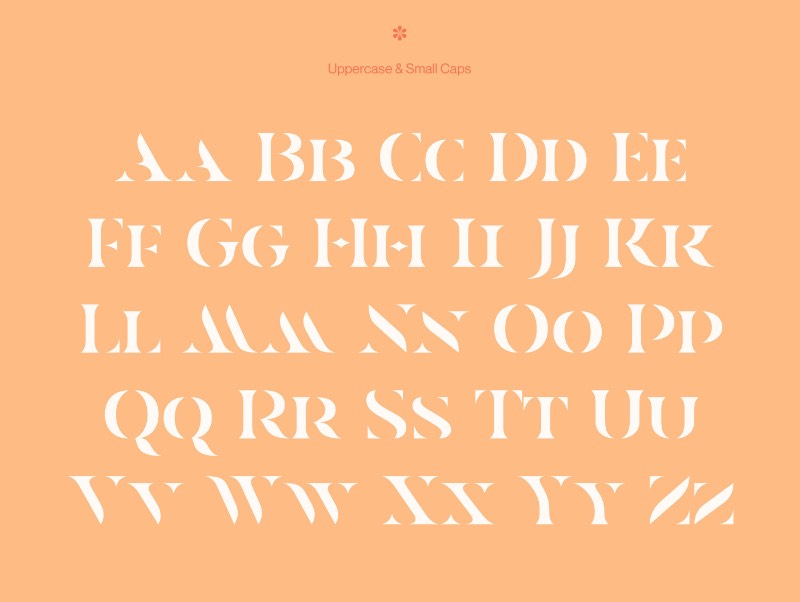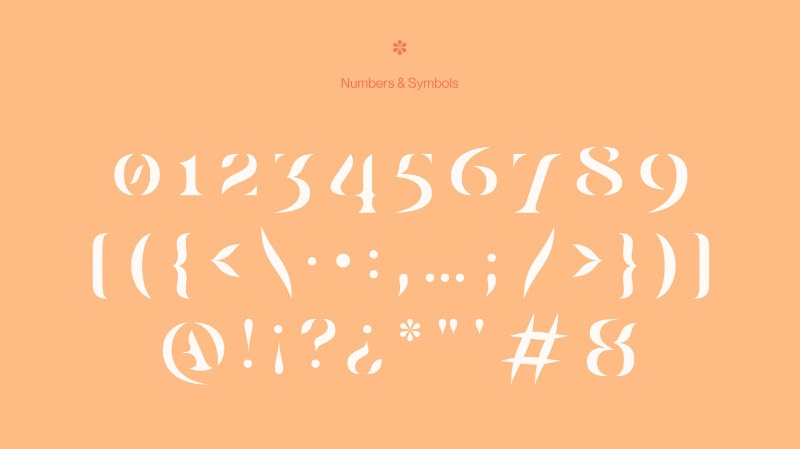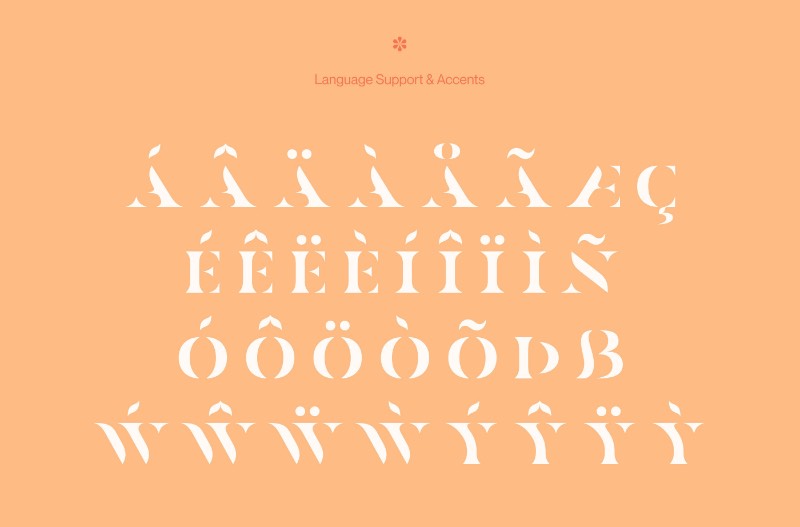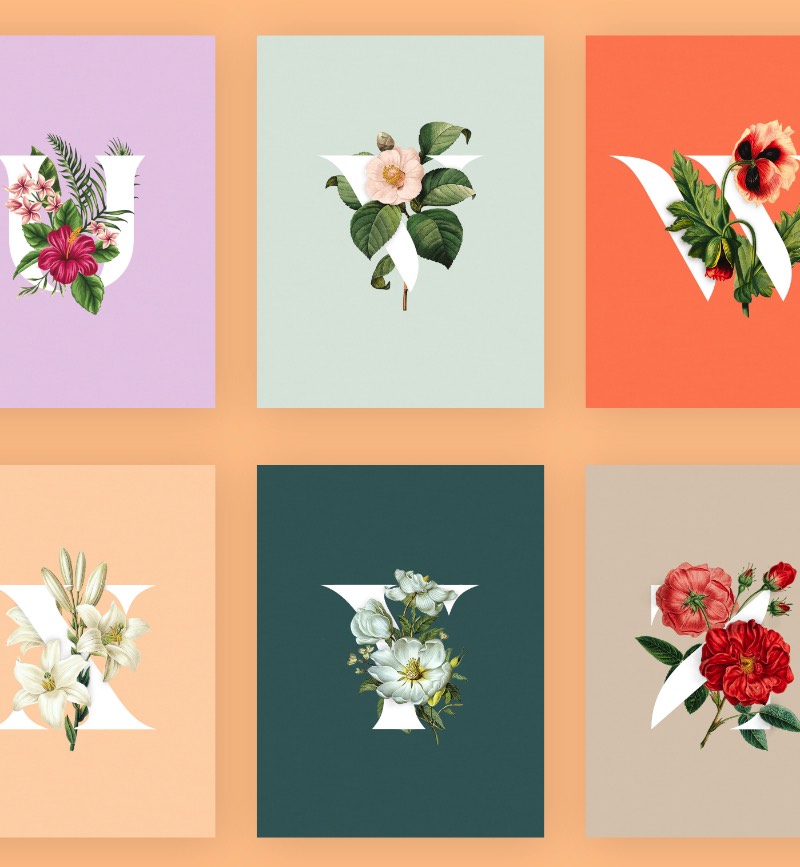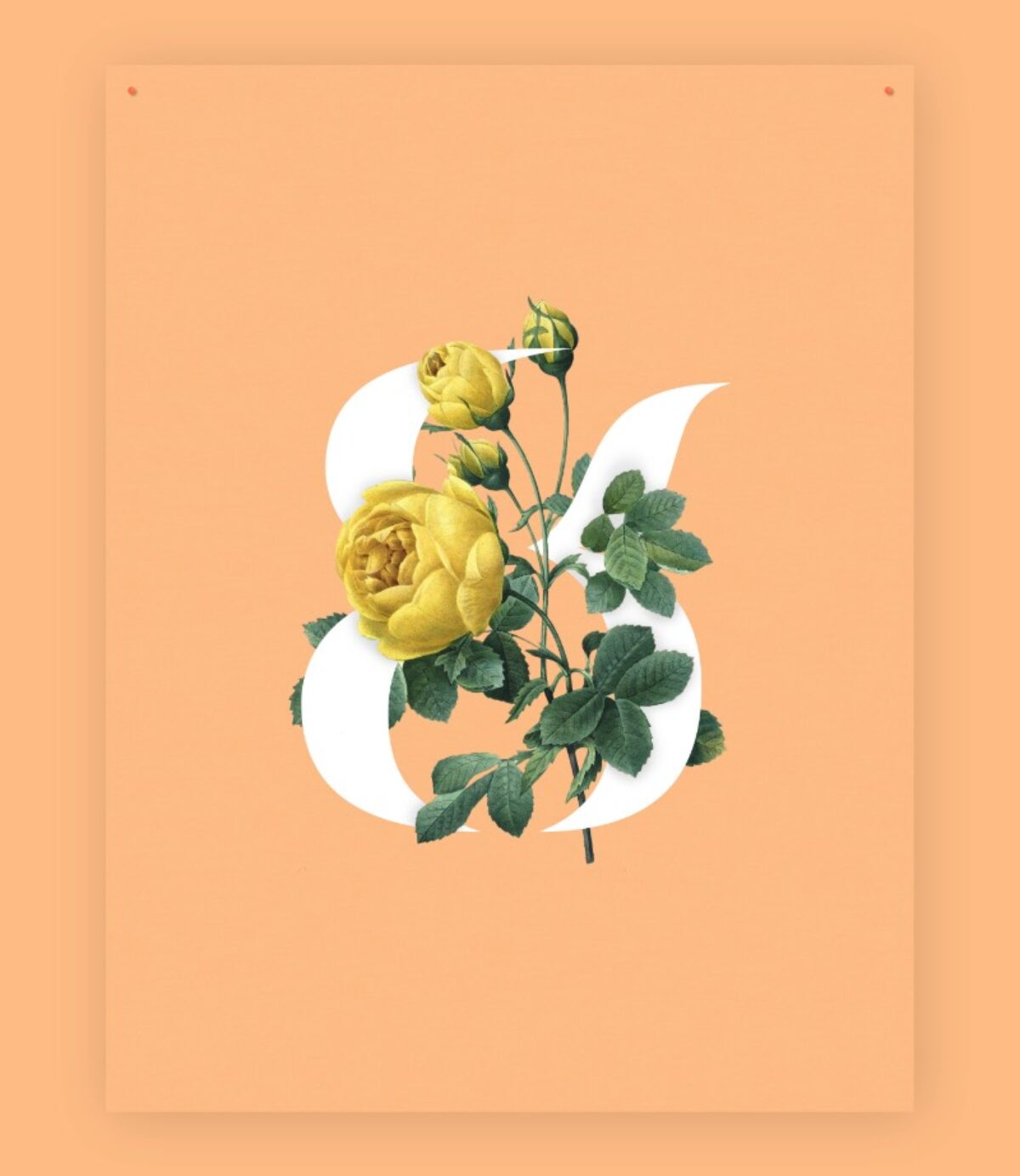
Casa Stencil de Mathieu Desjardins é a Fonte Gratuita da Semana
Casa Stencil é uma belíssima fonte stencil que é apresentada com curvas elegantes que apresenta quase um senso de erosão. Tudo por culpa da geometria de suas formas criadas pelo designer e diretor de arte canadense Mathieu Desjardins.
Casa Stencil é uma fonte que foi criada para mostrar um design único. Uma tipografia voltada para títulos e logos que merecem ser apresentados de forma especial. E isso tudo de forma gratuita quando se trata de uso pessoal.
Pessoalmente, gostei de ver algumas letras em particular e como que elas funcionam quando são apresentados de forma incompleta. Foi isso que eu gostei de ver na Casa Stencil e acho que você também vai gostar.
Casa Stencil is a beautiful, elegant stencil font that features soft curves and a sense of erosion. Its presence will definitely make your designs unique. It is made for all your title and logo needs. The font is free for personal use.